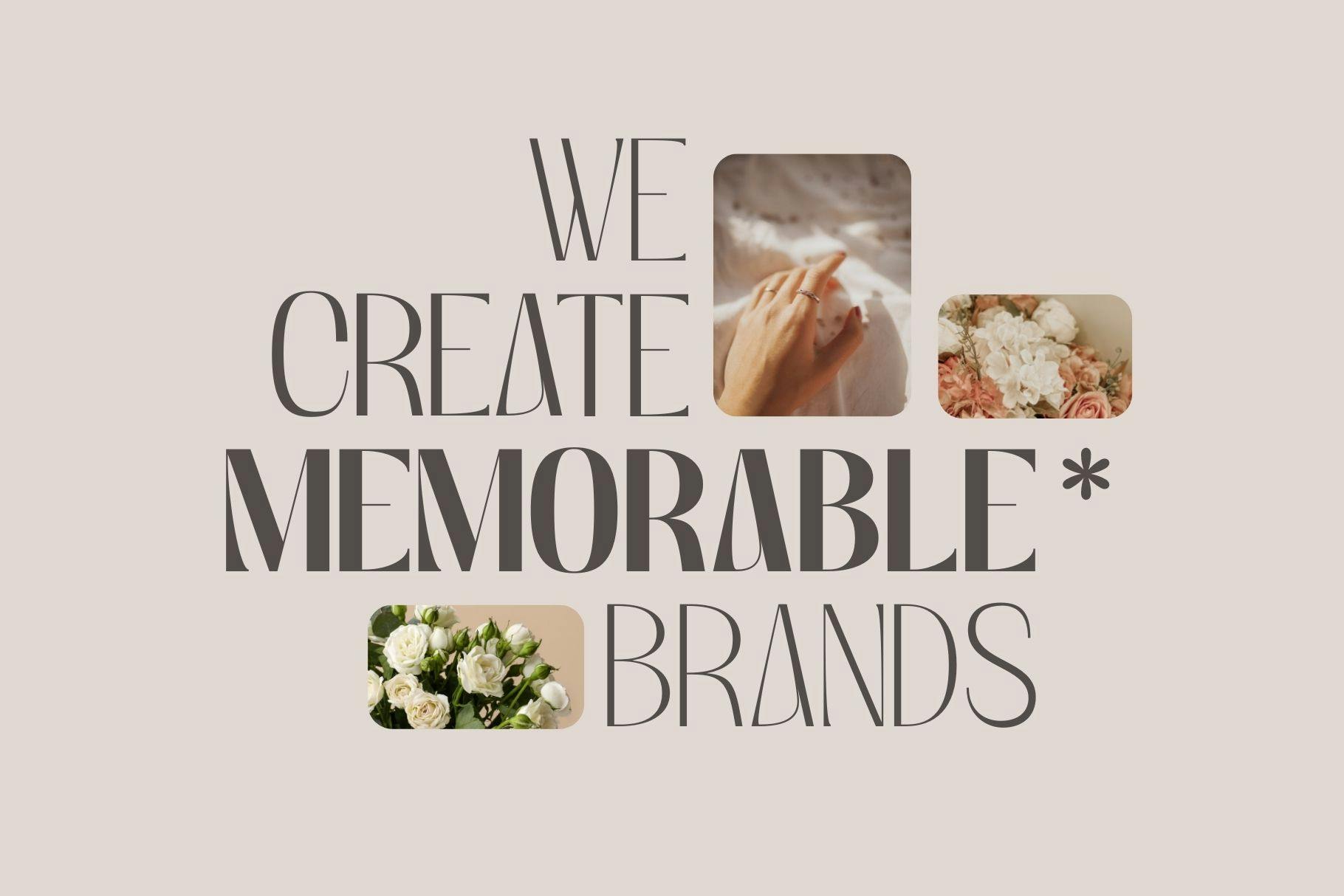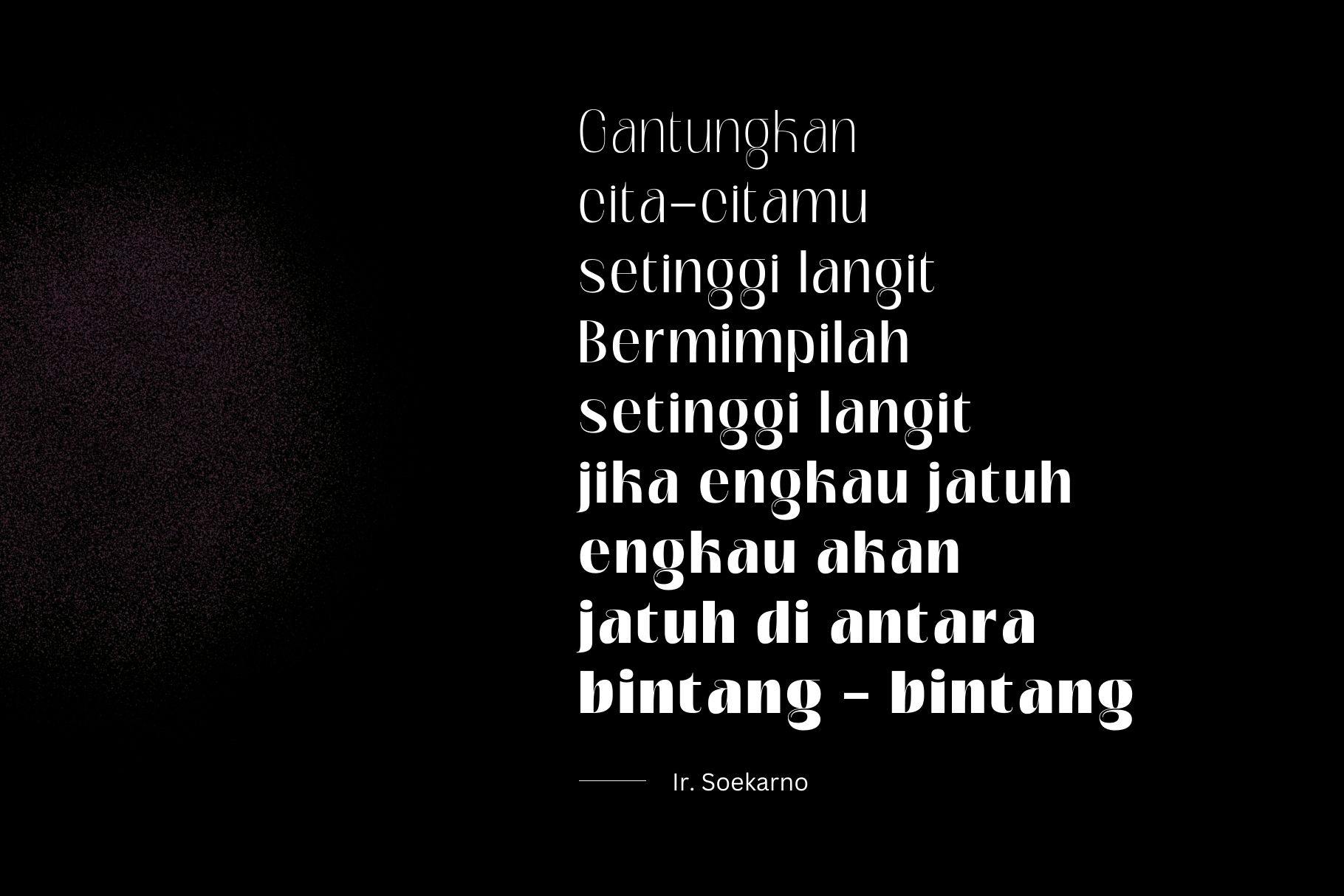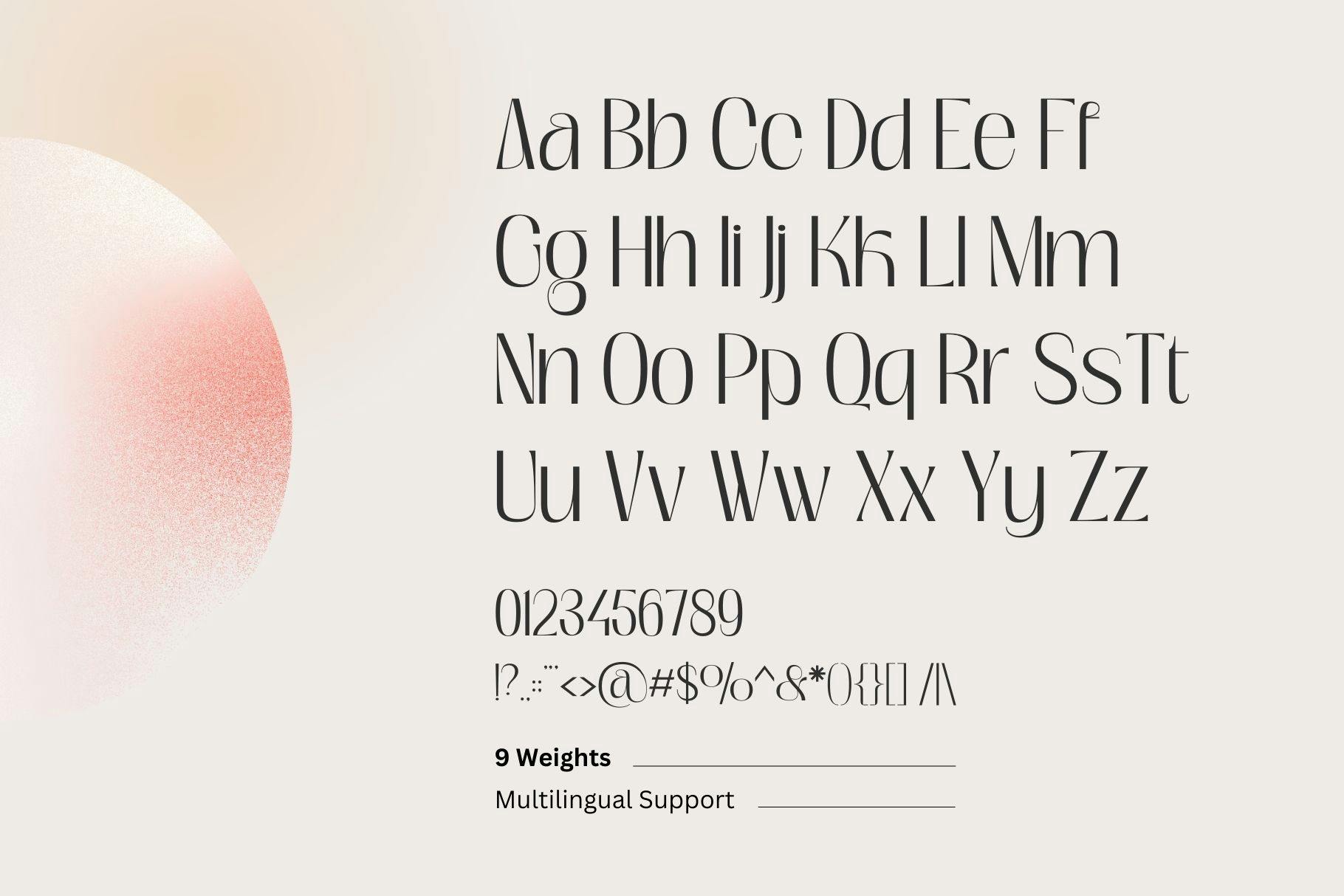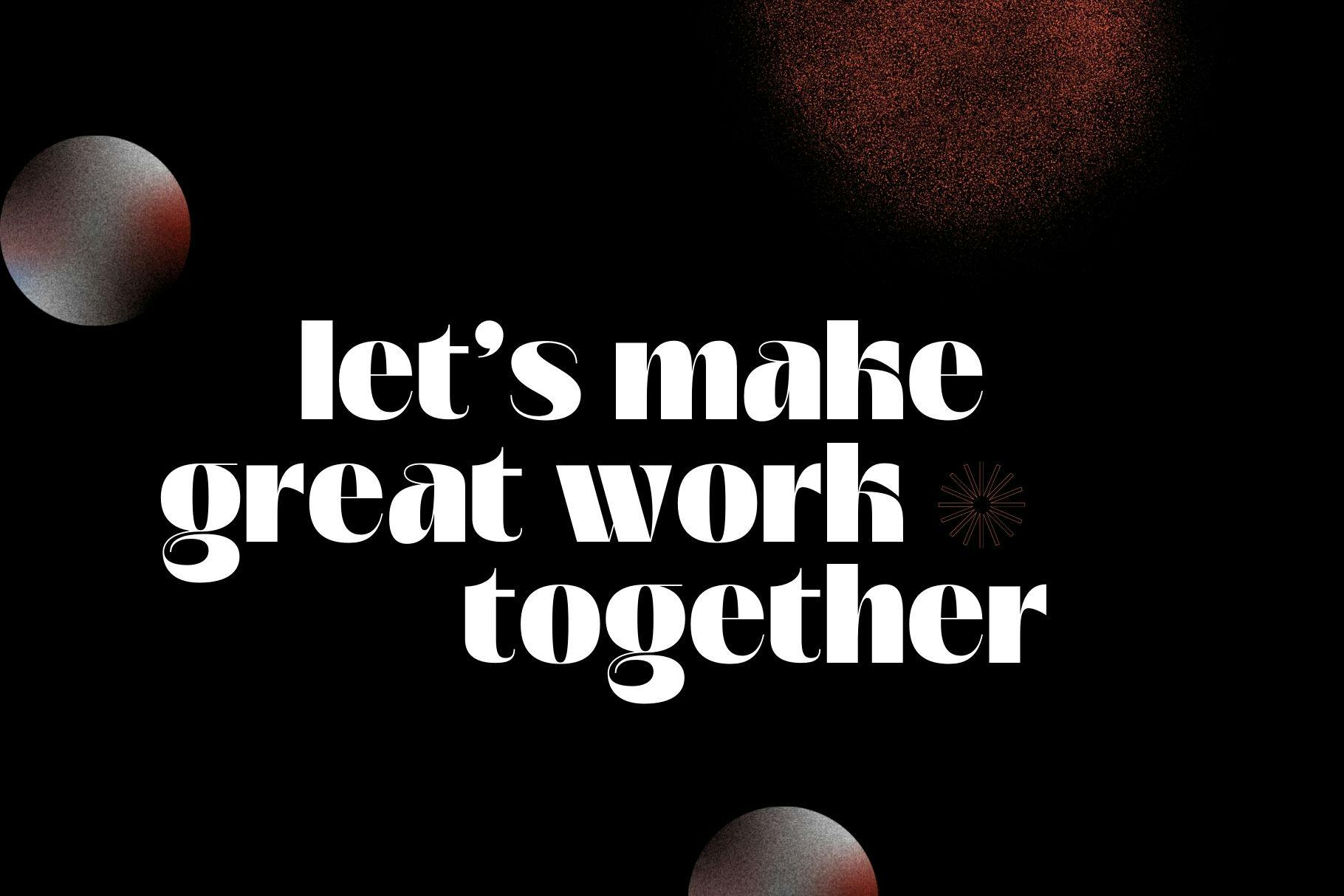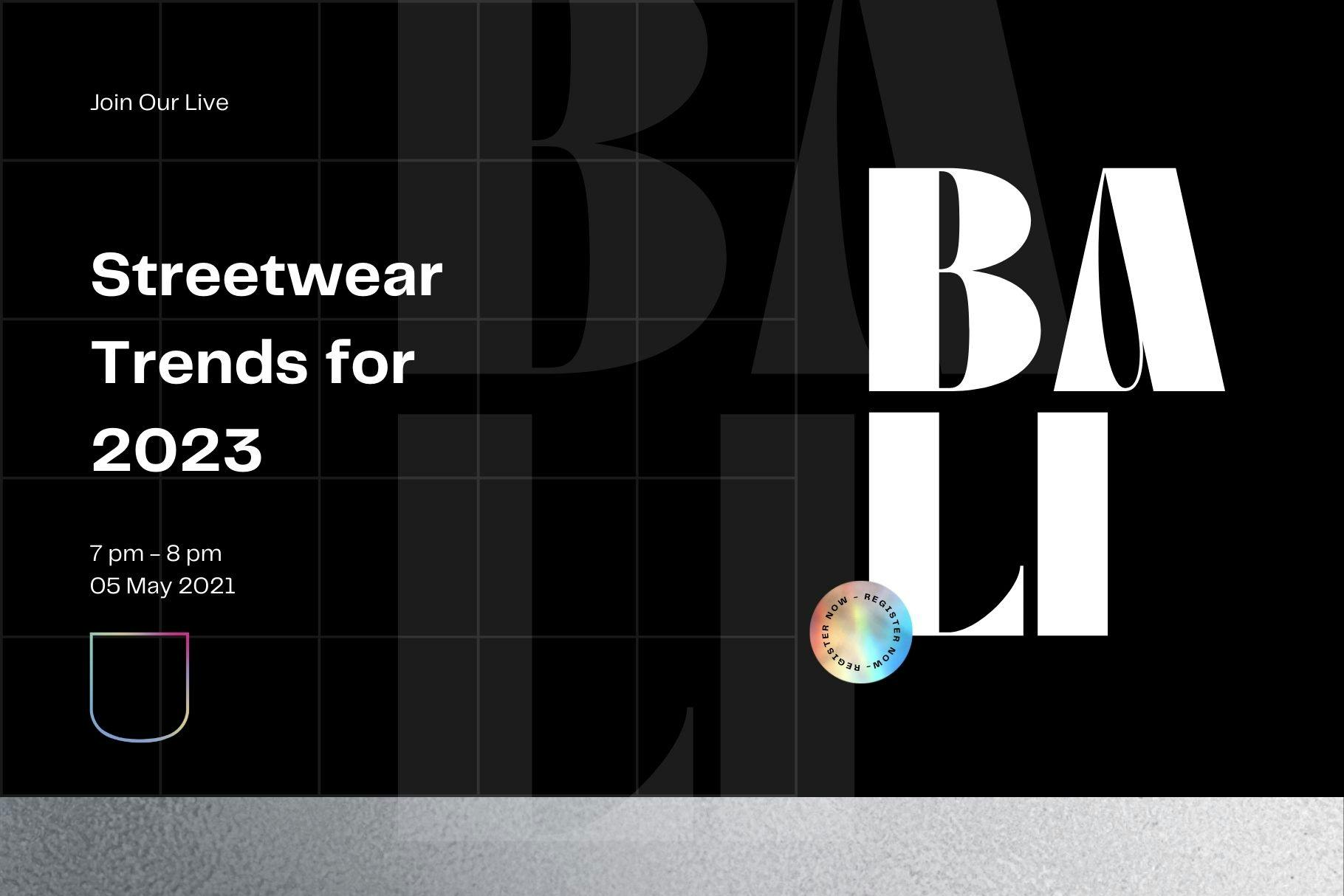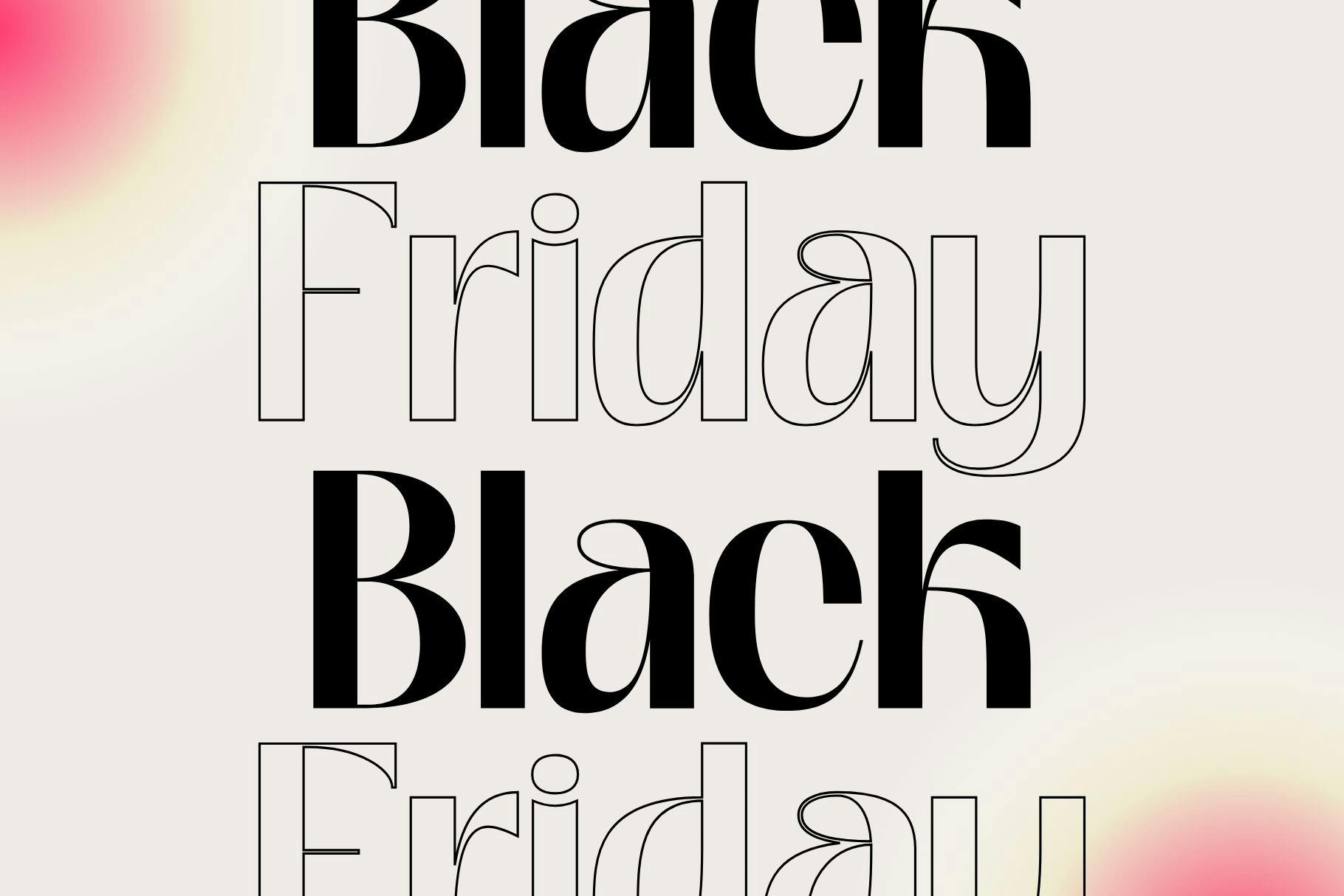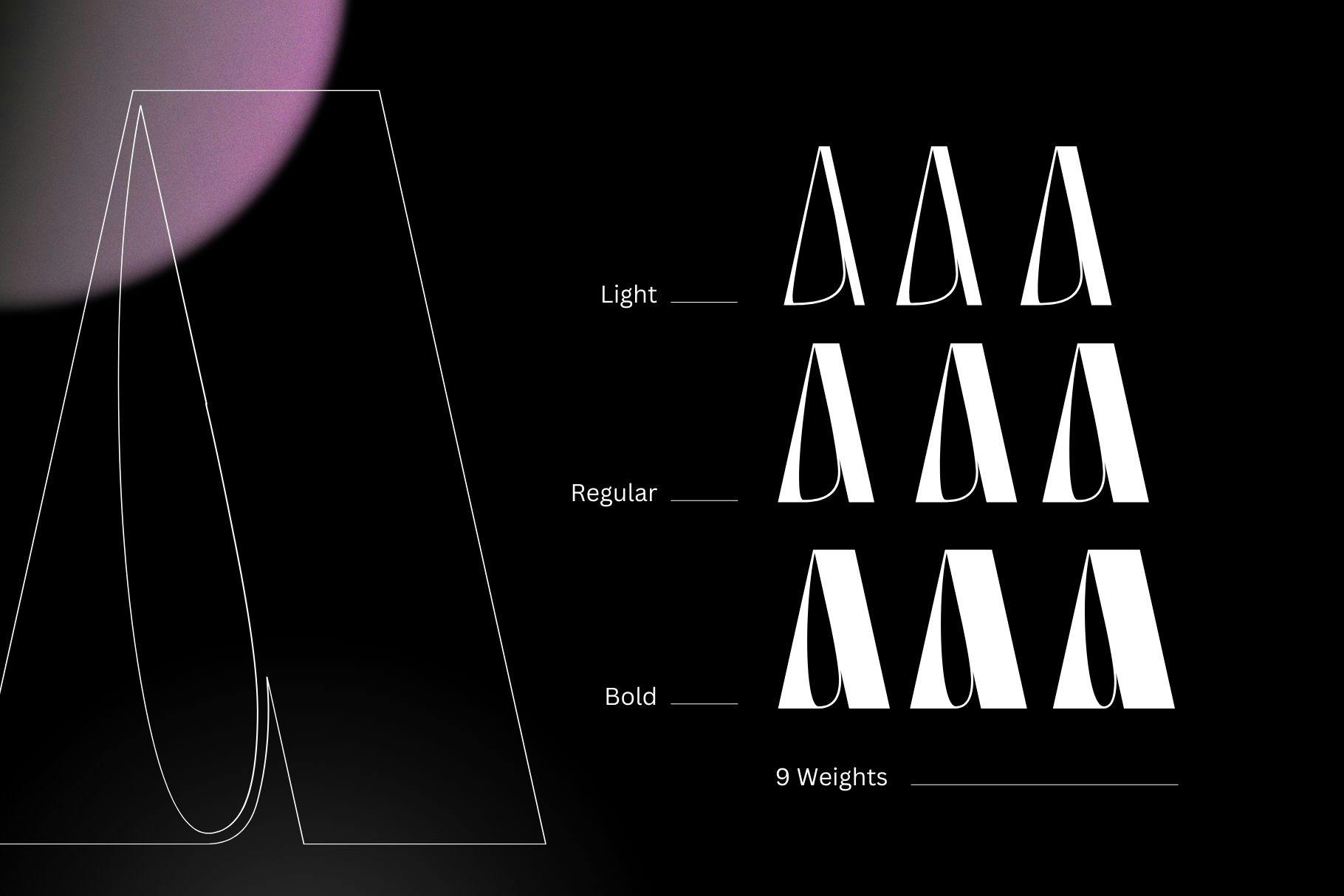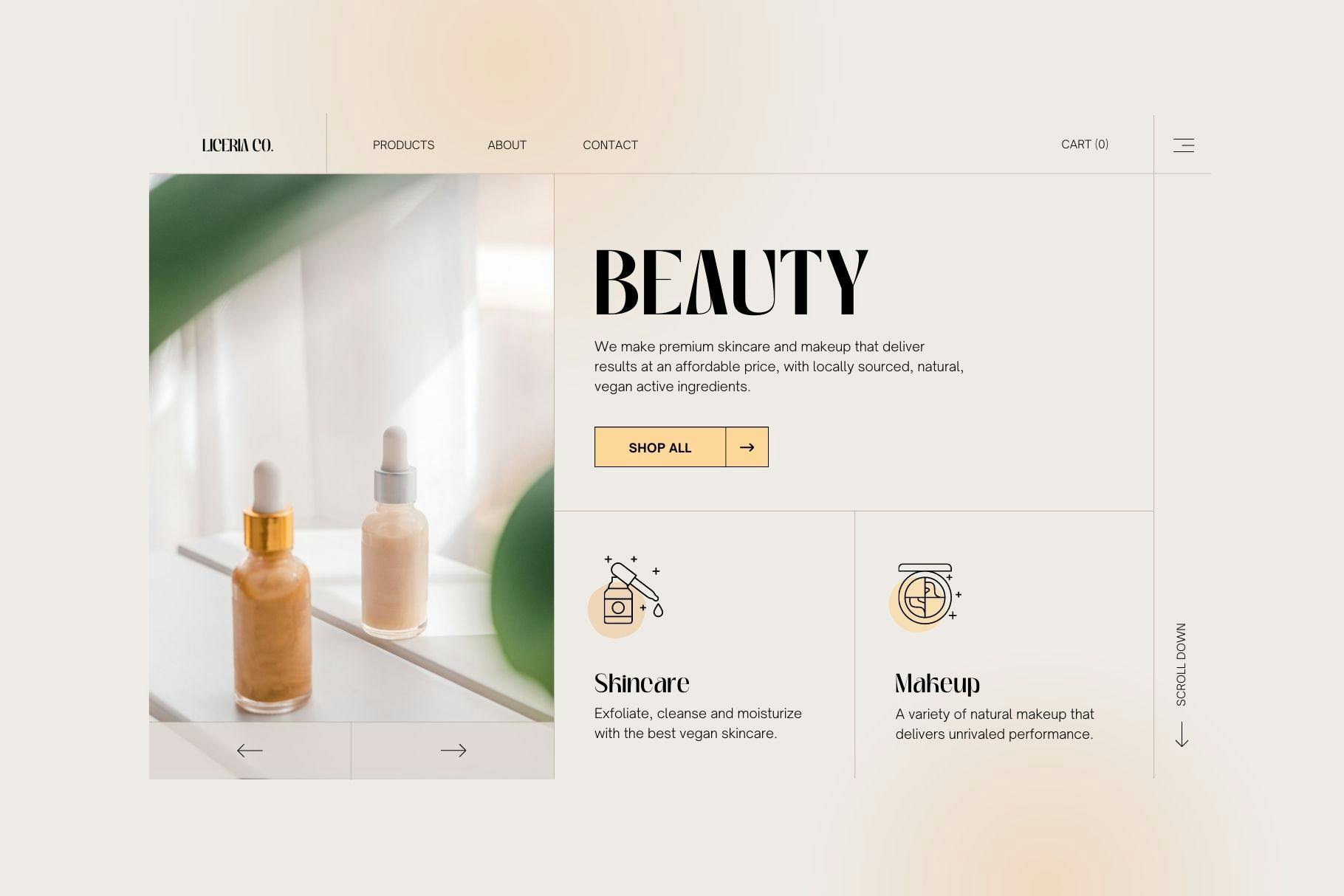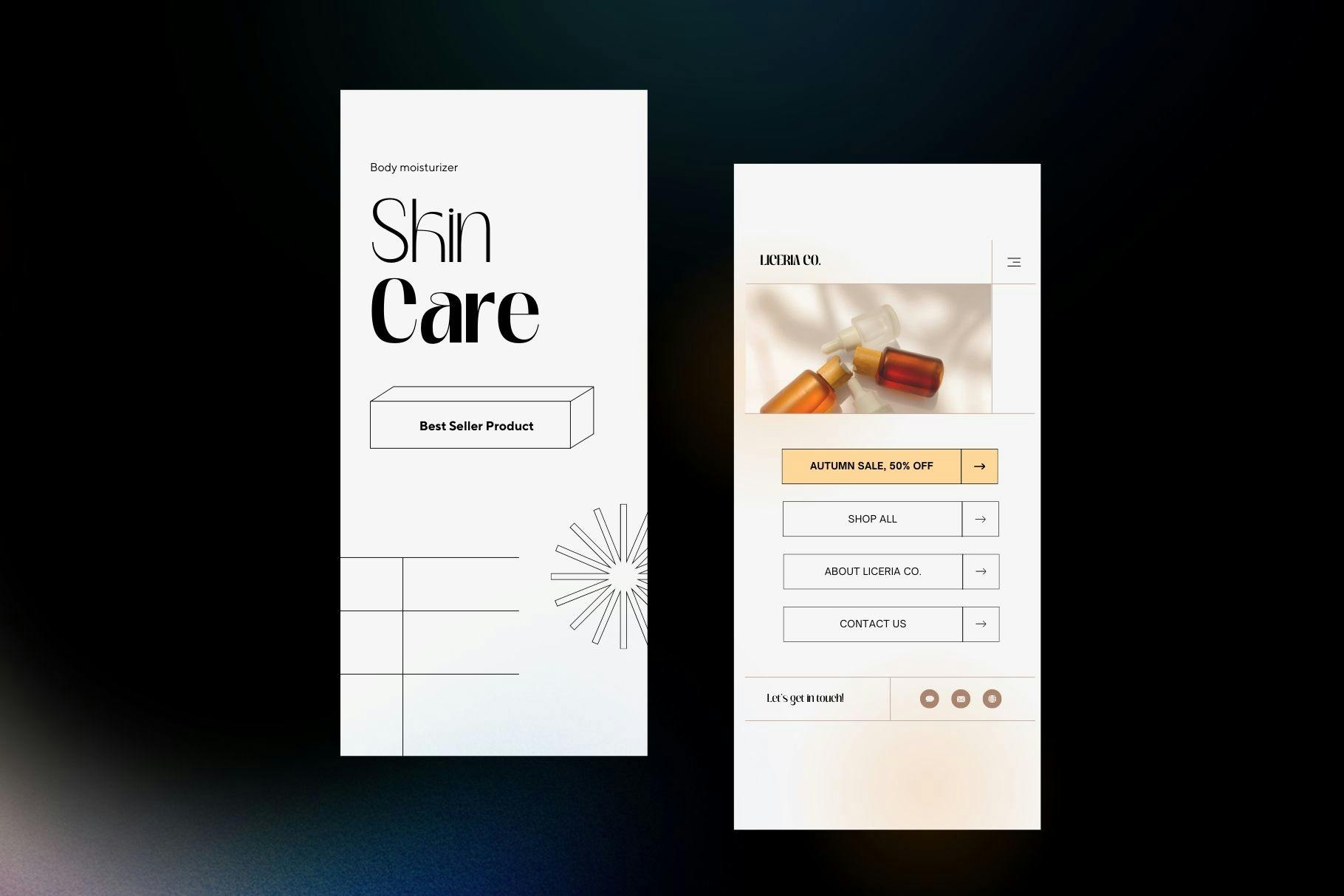
Aloha Magazine یک خانواده فونت منحصر به فرد و بازیگوش از نوع sans serif است که دارای 9 وزن مختلف میباشد.
این فونت هارمونی زیبای تایپوگرافی را برای تنوع پروژههای طراحی از جمله لوگوها و برندینگ، پستهای شبکههای اجتماعی، تبلیغات و طراحی محصولات ارائه میدهد.